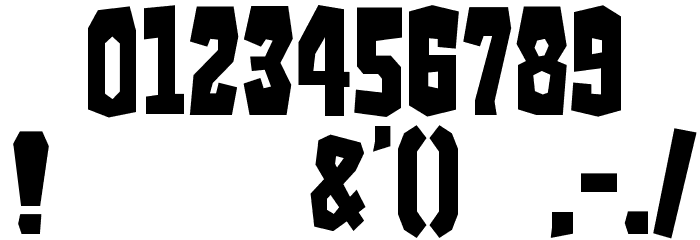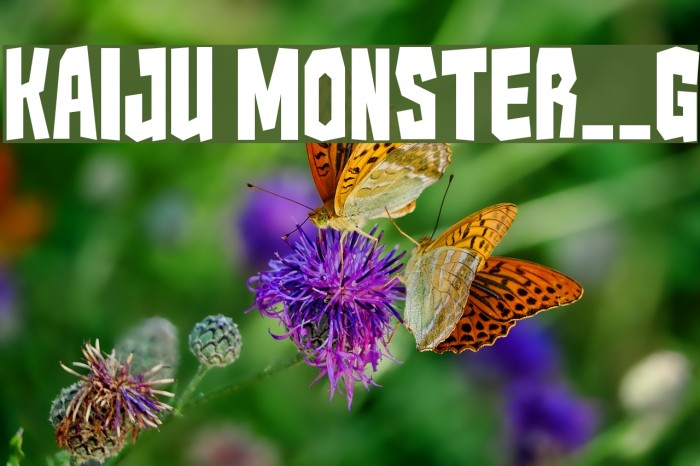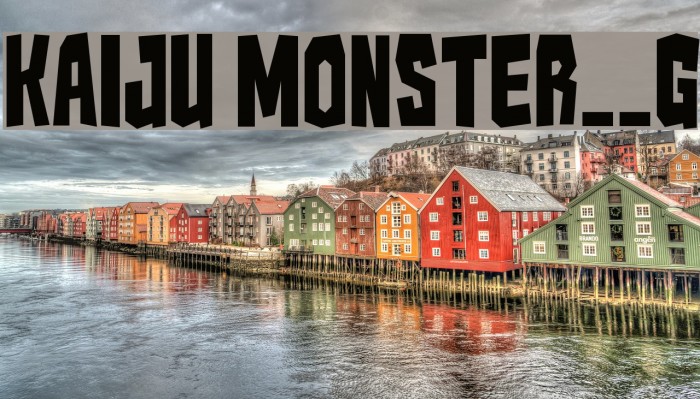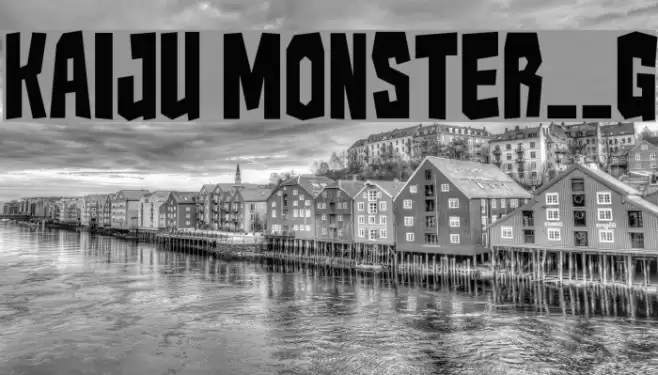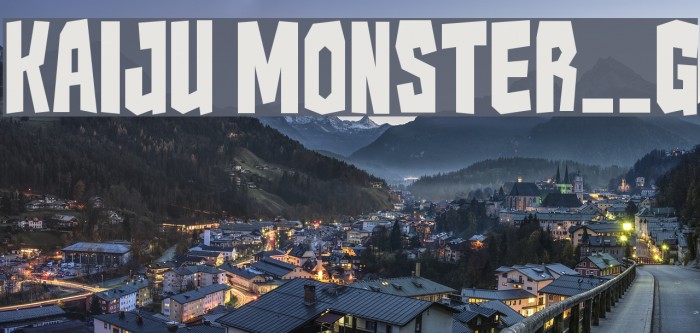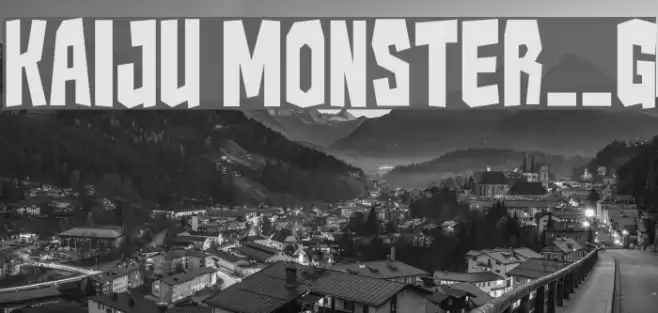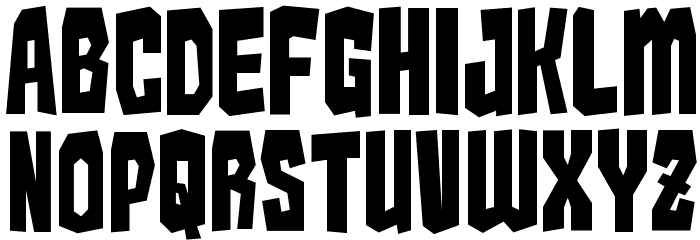
Kaiju Monster__G Font
✎ Thick
| Рекомендуемые проекты | Perfect for movie posters, video game titles, comic book covers, and branding for products targeting a bold and adventurous audience. |